Skiltadellur hér og þar
Svona til að koma mér af stað aftur langar mig að byrja á því að bísnast aðeins yfir skiltum hér og þar. Ég vil alls ekki vera að stilla mér upp sem einhvers konar leturlöggu, en þess vegna er dálítið gaman að minnast á skiltið á skrifstofuhúsi Ríkislögreglustjóra.
Ég ek all oft fram hjá því húsi þar sem það stendur rétt við Sæbrautina. Mér er lengi búið að finnast eitthvað bogið við þetta skilti en af því maður er á ferð í bíl var ekki svo auðvelt að skera alveg úr um hvað var að.
Aldrei þessu vant opnaði ég DV í dag og þar var þessi fína mynd af skiltinu og þar fer ekki milli mála hvað er að… ef þú vilt giska núna skaltu grúfa hendinni yfir textann og rýna í þetta.
Einhverjum hefur orðið aðeins á í messunni snúið U-inu spegilvent. Allir geta nú gert mistök.
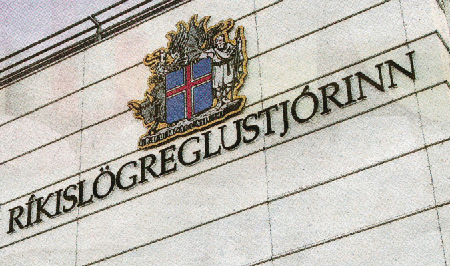
Letrið sem notað er er Palatino og til samanburðar má sjá það hér:
Annað skilti, sem stingur dálítið í augu er GRAND, merkingin á Grand hótelinu nýja og stóra.
Það er engu líkara en að þetta hafi verið slegið inn á tölvu með vinstri jöfnun, prentað út og breytt í skilti. Hér hefði gjarnan mátt leggja aðeins meira undir í vali á letri og frágangi. Það er eitthvað svo innilega skakt við þetta.